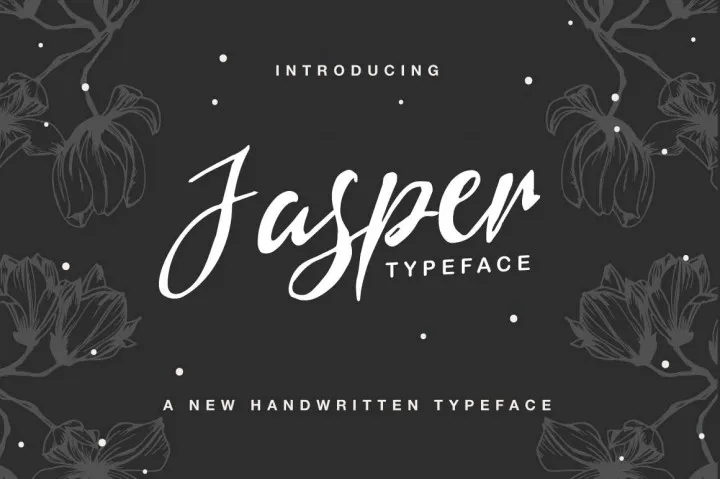
Jasper Brush Font – Download Grátis
A fonte ‘Jasper Brush Font’ é perfeita para quem busca uma personalidade única e moderna em seus projetos. Trata-se de uma elegante tipografia script com traços arredondados e um toque jovial, que inclui algumas novas formas exuberantes. Ideal para usar em roupas de marca, logomarcas, textos impressos em cartazes ou notas, convites de festa, sobrepostos a imagens de postagens no Instagram, cardas de presentes, embalagens de produtos e até mesmo capas de livros e design gráfico. Esta font é particularmente indicada para qualquer projeto que valorize o toque natural e pessoal, seja em cartões de apresentação ou até mesmo nos detalhes mais sutis do seu trabalho. A versatilidade da ‘Jasper Brush Font’ permite que você personalize ainda mais suas criações combinando alternativas de letras, criando mensagens intrigantes para seu design. Estamos certos de que esta fonte irá deixar sua marca no mercado dos recursos gráficos.